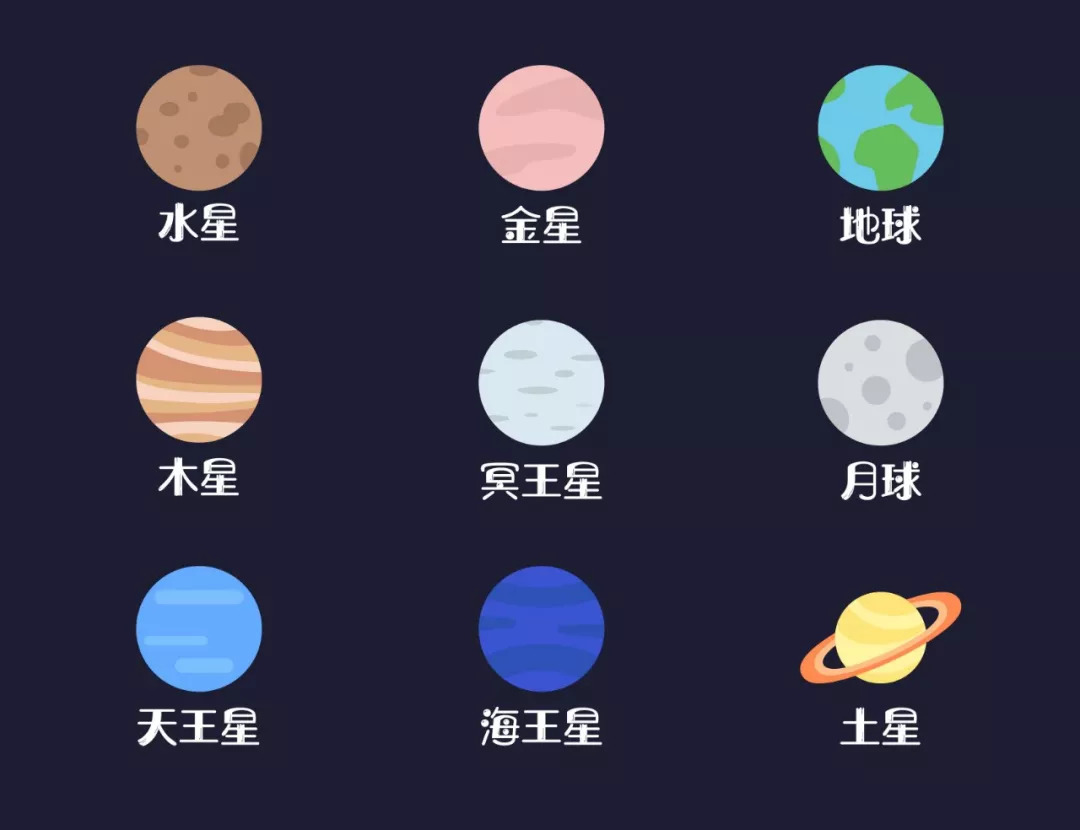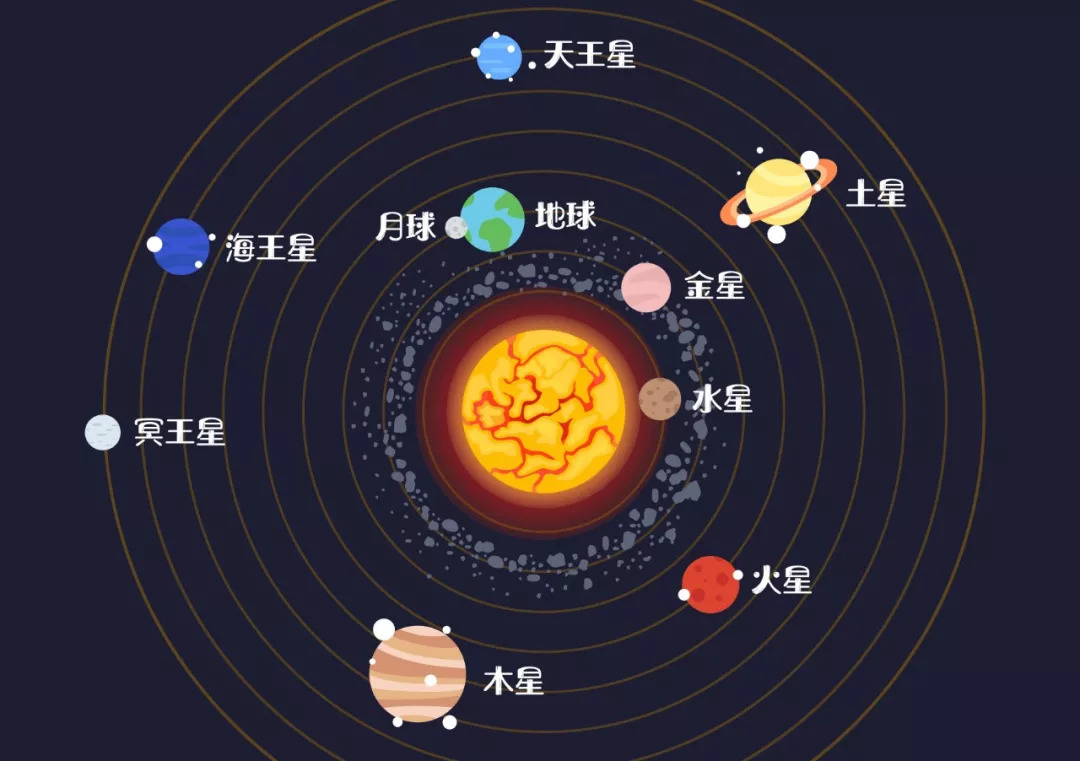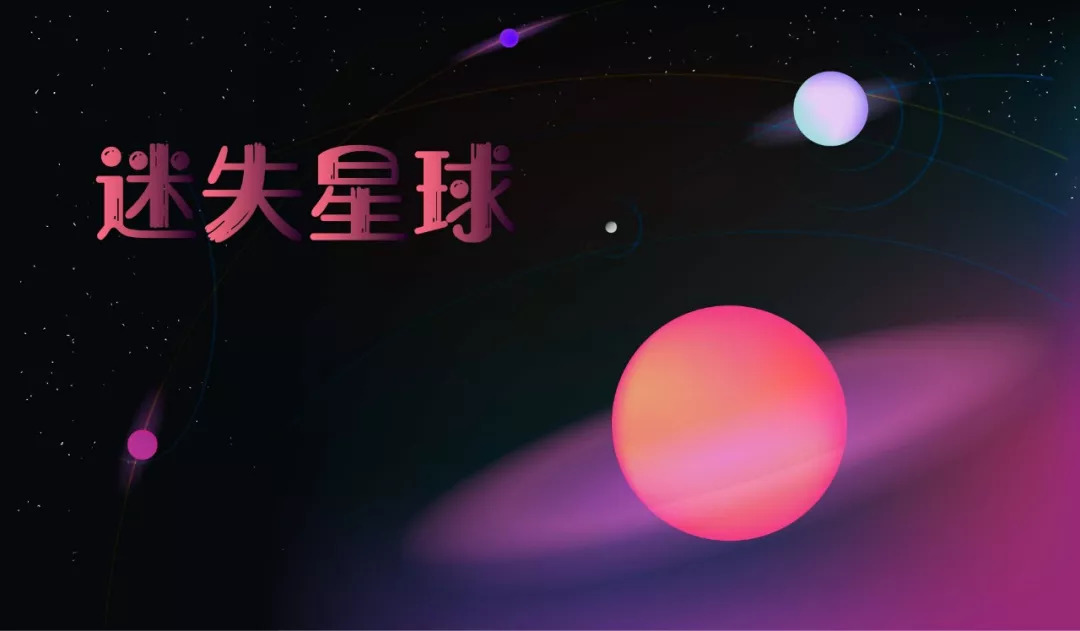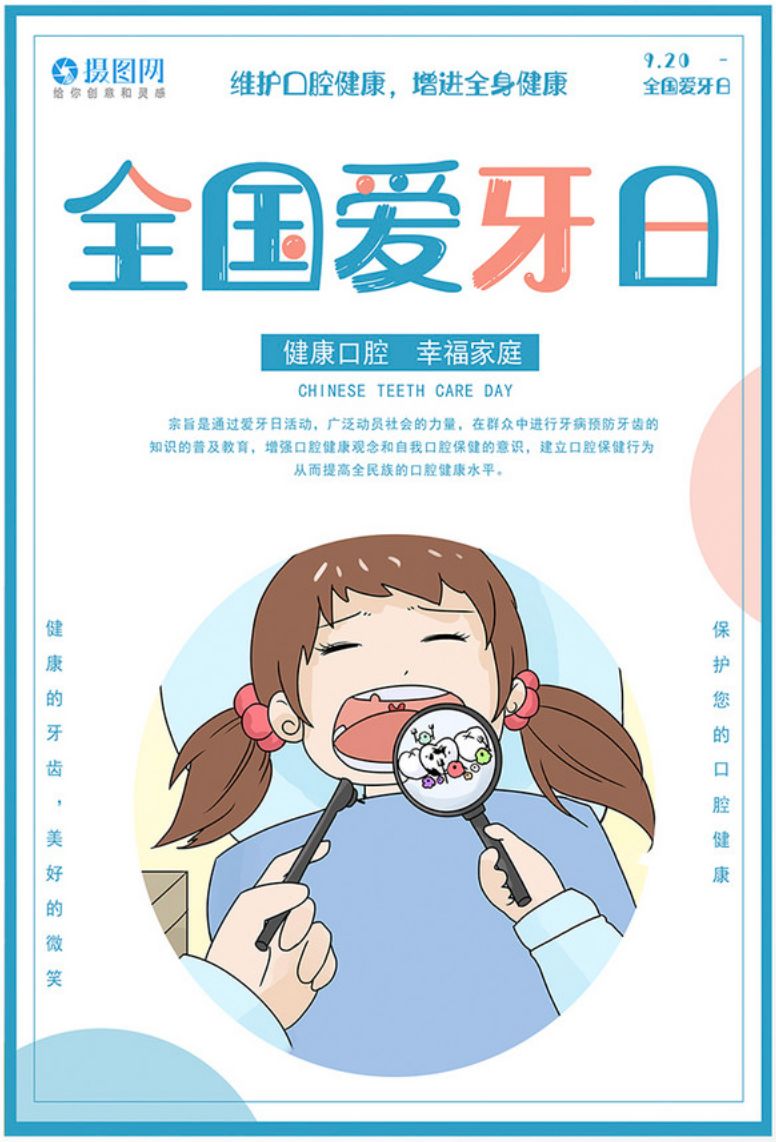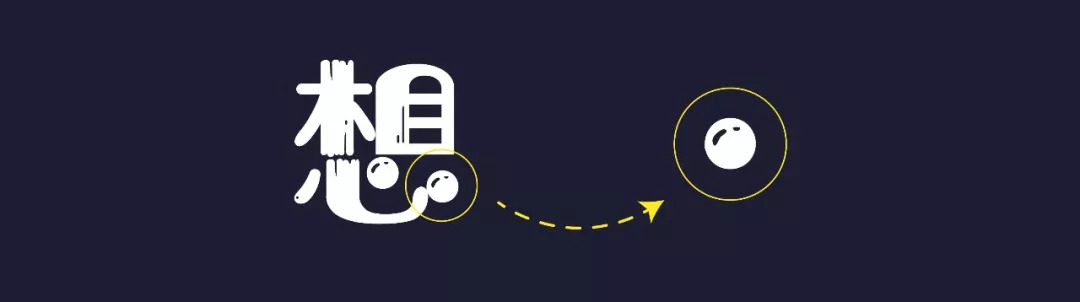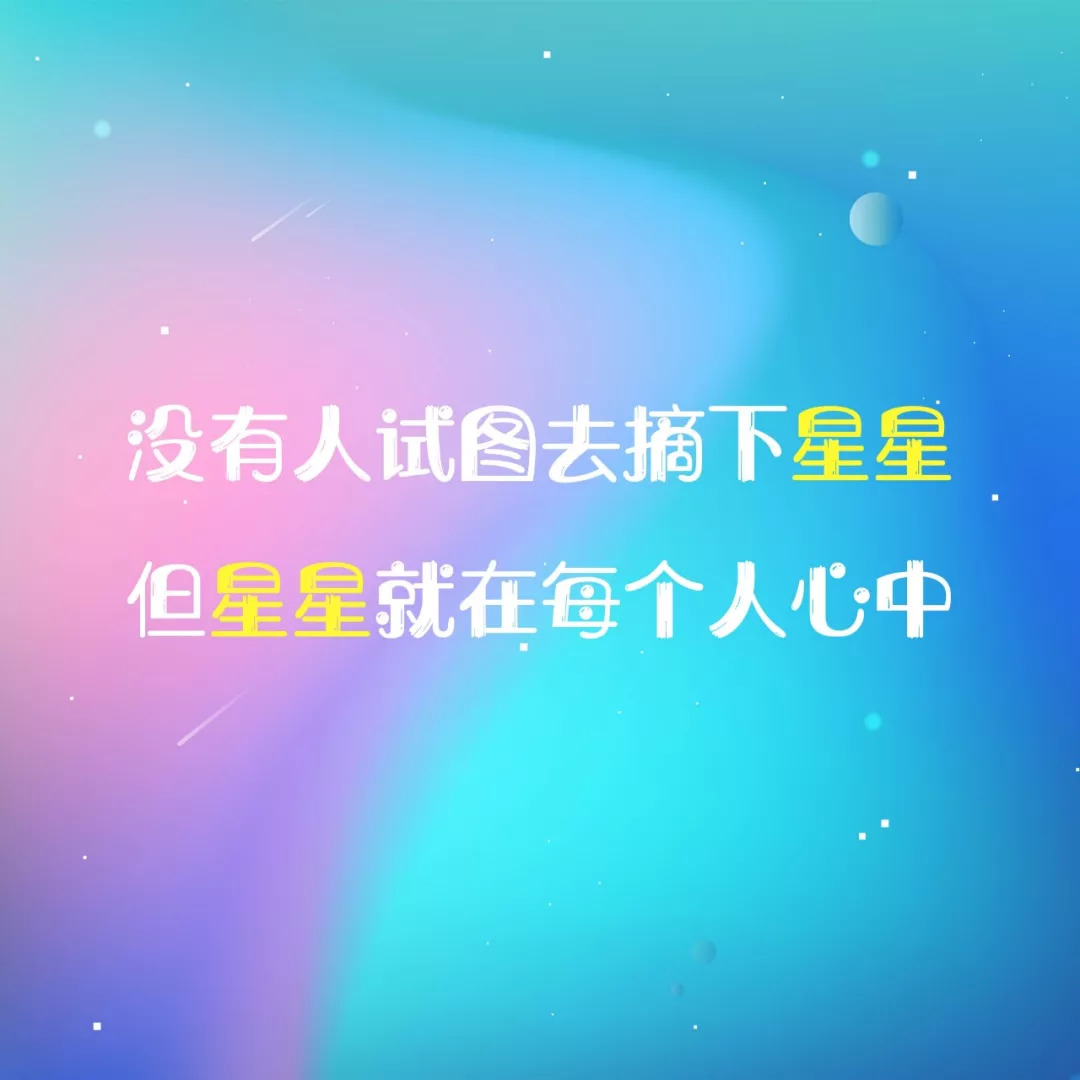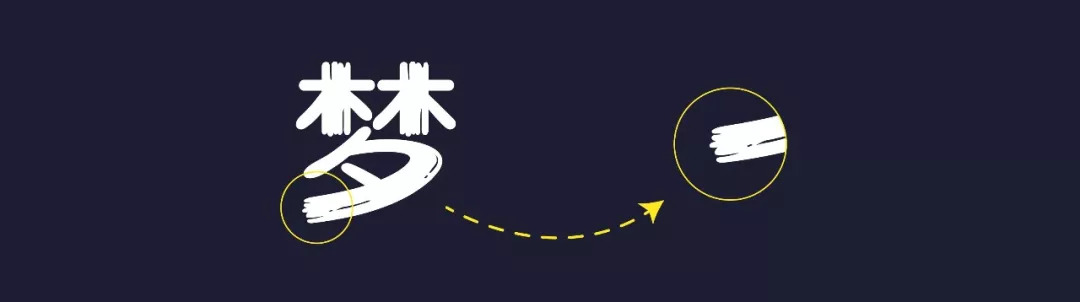
汉仪星球体介绍,汉仪星球体字体应用案例
在浩瀚无垠的宇宙中存在着无数的星球,他们由各种不同的元素组成。
他们或胖或瘦,或大或小但都是在自己地盘上混的“风生水起”。但你有没有思考过这样的问题:为什么星球都是球形呢?而不是其他形状?
这就要从牛顿发现的万有引力说起来了,牛顿发现所有的物质都有相互的吸引力,这种引力和物质的质量与距离有着简单的关系:物质愈多,质量愈大,吸引力就愈大;物质之间距离愈近,引力则愈大。说白了就是两个人飘在太空,越重的人越容易吸引另一方靠近自己。
以地球为例,地面所有物质都被地球的引力所吸引,在无重力的空间中地球引力会把一切物质拉向地心从而使地球看起来是个类球体。
这也就是为什么大家观测到的大星体都是球状,当然通过这个理论我们也可以简单得出一个结论,质量越小则越不容易形成球状,比如平均直径只有525千米的灶神星(地球平均直径约是它的24倍),大致是一个不规则的椭圆状。
而更小的行星,形状自然更加有意思,比如有着“胖香蕉”之称的爱神小行星,其长33公里,厚度仅有13公里。
还有就是由9169个汉字及939个西文与符号组成的——汉仪星球体,这小巧的体积在万有引力的作用下自然形成了更加有趣可爱的外形。
圆鼓鼓的外形搭配上点点高光,像极了那夜空中一颗颗闪亮的星星。
参差不齐的笔刷感,好像一颗彗星拖着它那长长的尾巴从天空中划过。
而这样一颗可爱童趣的“星球”,